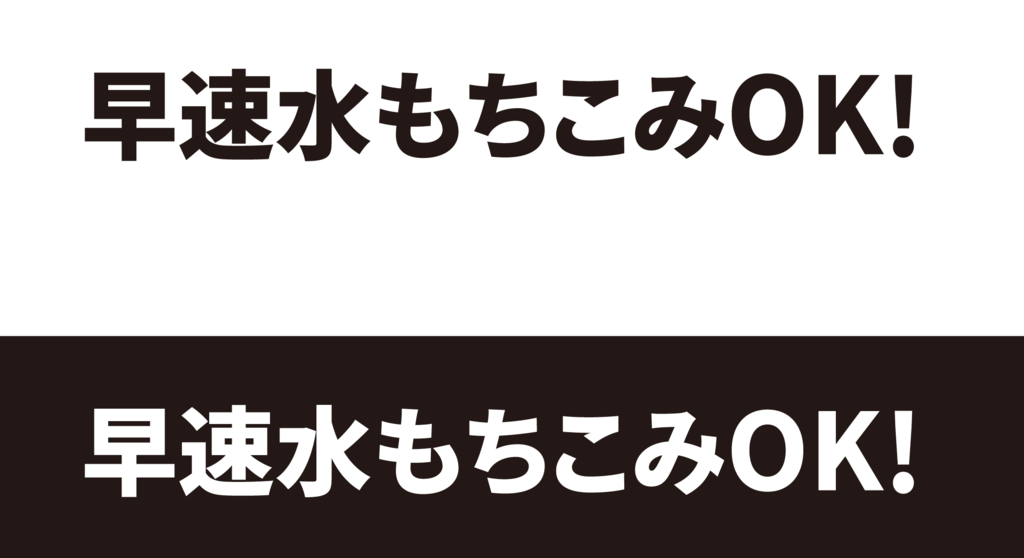
源暎ゴシックP
「源暎ゴシックP」は、オープンソースフォント「源ノ角ゴシック」の派生フォント。
「源ノ角ゴシック」ではYouTubeやニコニコ動画などのテロップ向けに等幅だった仮名文字をプロポーショナル化し、限られた領域に多くの文字を詰め込めるように改良。
また、日本語の文字と比べて小さく映る半角英数字を半角と全角の中間のサイズへ拡大し、文字列で見たときのまとまり感と統一性に加えて、瞬間的な読みやすさが向上している。画像は全てHeavyで作成。